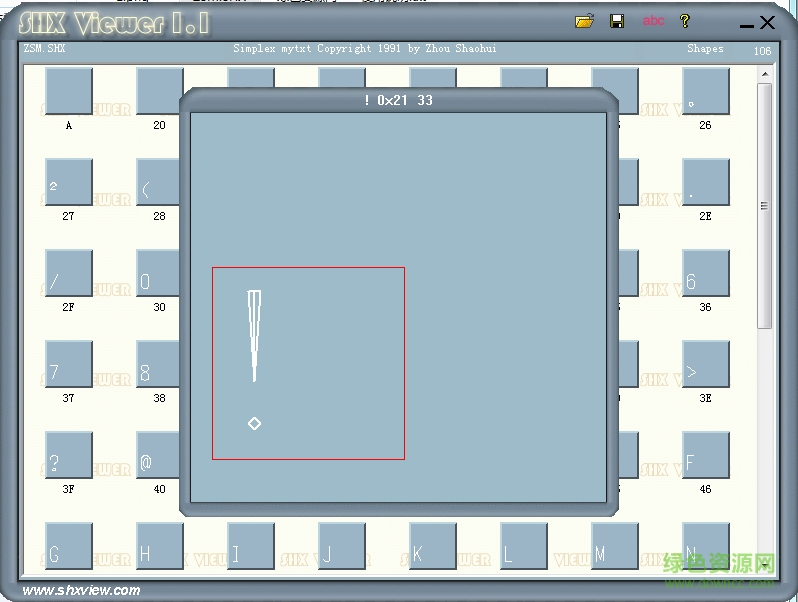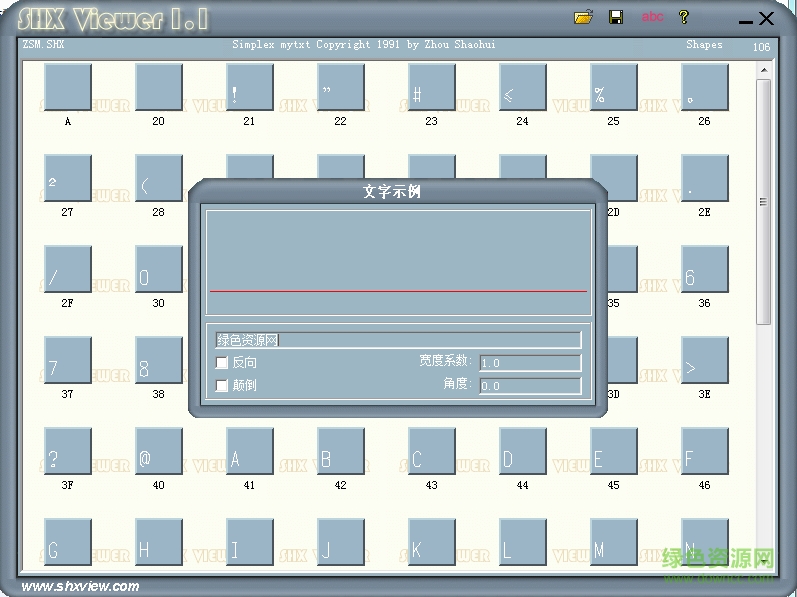
zsm.shx是一款cad形字體,有106個(gè)字符,支持英文字母、標(biāo)點(diǎn)符號等輸入,有著流暢的筆觸,是平面設(shè)計(jì)、廣告創(chuàng)意中使用鮮明立體的助手,來綠色資源網(wǎng)即可免費(fèi)下載!
在autocad中,充斥著各種大字體、形字體、小字體等,這些讓你的藝術(shù)設(shè)計(jì)的文字或字母的標(biāo)識更有顯著性和美觀性,zsm.shx就是其中的形字體系列,有著豐富的符號,包括常用的、數(shù)學(xué)類等。